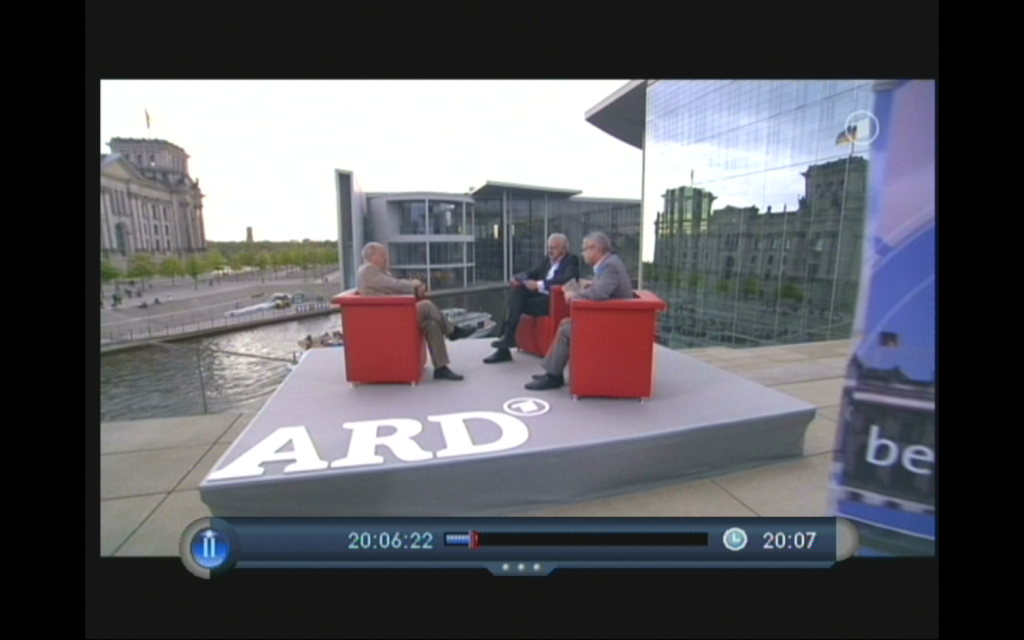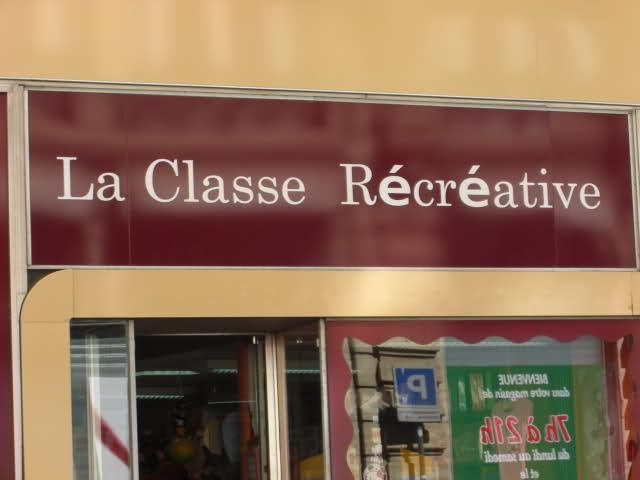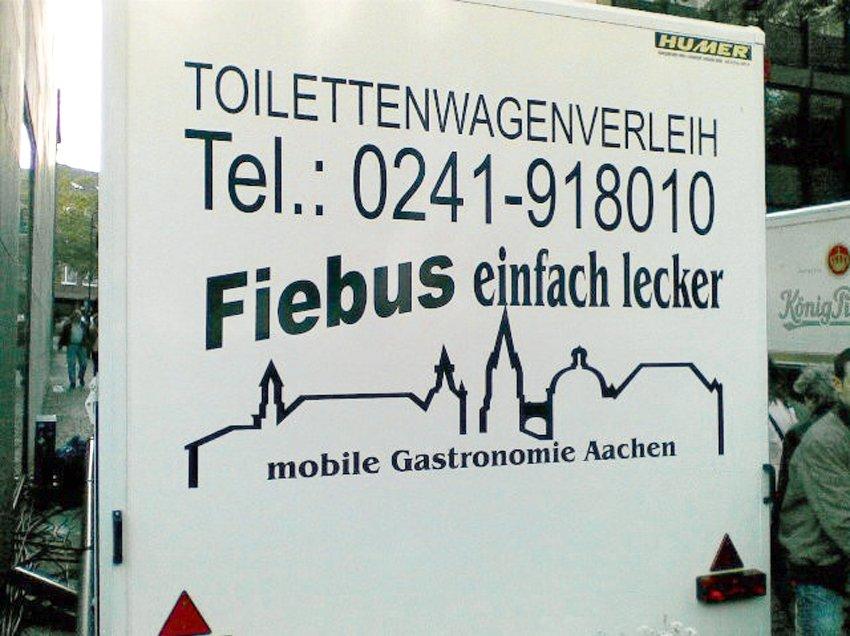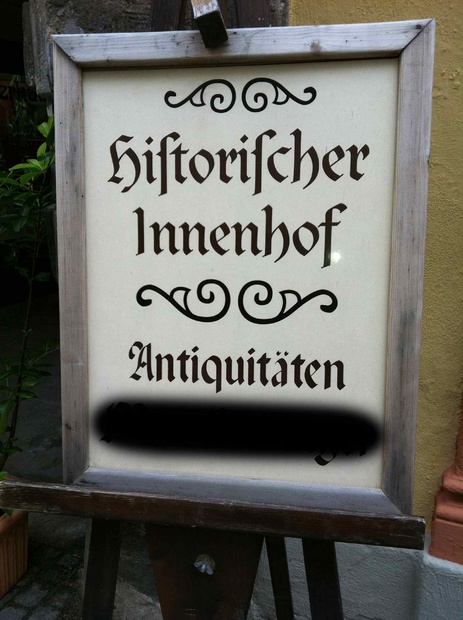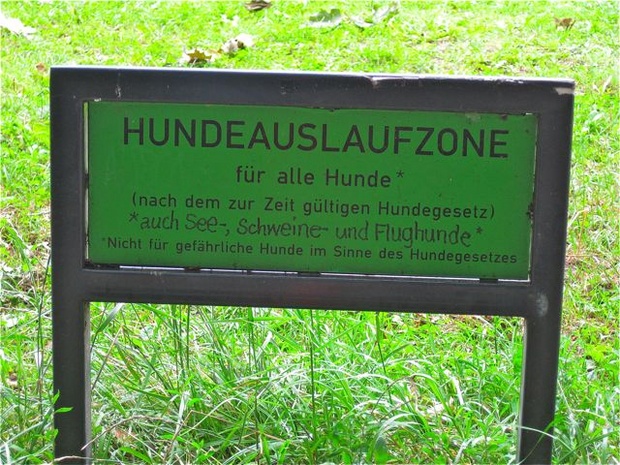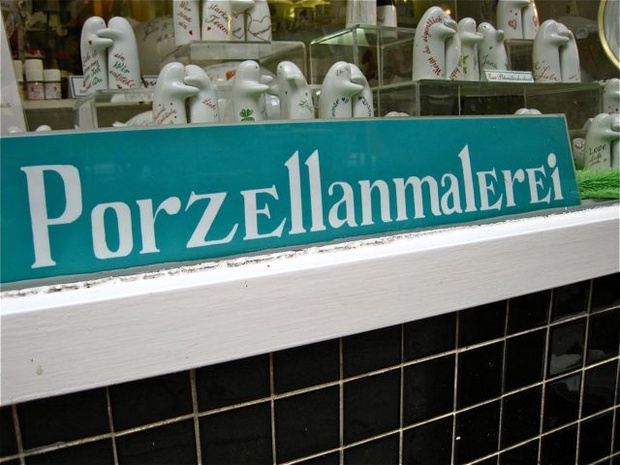
Vielleicht ist man vorher beim Werbefuzzi des Dorfes gewesen und hat nachgefragt, ob er nicht ein paar Foliereste für den Kindergarten übrig habe. Ich kenne solche Nachfragen jedenfalls.
Und dann: Nagelschere? Teppichmesser? Schablone aus Buchstaben, die aus der Zeitung ausgeschnitten wurden? Kann nicht mal jemand da hinfahren und eine Reportage machen? :-P
Vielleicht ist man vorher beim Werbefuzzi des Dorfes gewesen und hat nachgefragt, [...]
... was so ein schild denn koste. dem preis fand er dann unverschämt hoch, und aus trotz ... fertig das schild.
Im Spiegel gefunden …
So gefunden in Montpellier, Südfrankreich …
Ziemlich kreativ find ich :hammer: schließlich soll man ja nur nicht Buchstaben aus ähnlichen Schriften mischen, um Lücken im Zeichensatz auszubessern :oops:
Sehr cool! Warte mal, sowas ähnliches ist mir doch gestern auch über den Weg gelaufen. Waren zwar keine so unterschiedlichen Schriften wie bei Deinem Beispiel, aber dafür waren die e-Minuskeln offensichtlich aus … ;-) In dem Laden würde ich mein Porzellan jedenfalls lieber nicht beschriften lassen ...
Ja da würde ich mein Porzellan auch schlicht weiß lassen – ist eh schöner.
Das z (oder kleines Majuskel-Z?) sieht auch seltsam aus …
Wenn Du wüsstest, wie der Rest des Schaufensters aussieht … ;-)
Steht das Schild vor dem "Brandenburger Haus"?
AAAArgh, was war denn da los? Der Beauftragte zur Logo-Positionierung im Sommerurlaub? Ich meine mich zu erinnern, dass der Ausgleich der Buchstaben in vergangenen Sendungen auch schon einmal besser war.
Na ja, die brauchten halt genug Platz für die Sessel. ;-) Wir sollten vermutlich dankbar sein, dass sie die Buchstaben nicht gestapelt haben … Vielleicht wurde aber auch nur kurz vor der Sendung die Bühne noch mal feucht durchgewischt und keiner hat daran gedacht, alles wieder an seinen alten Platz zu schieben …